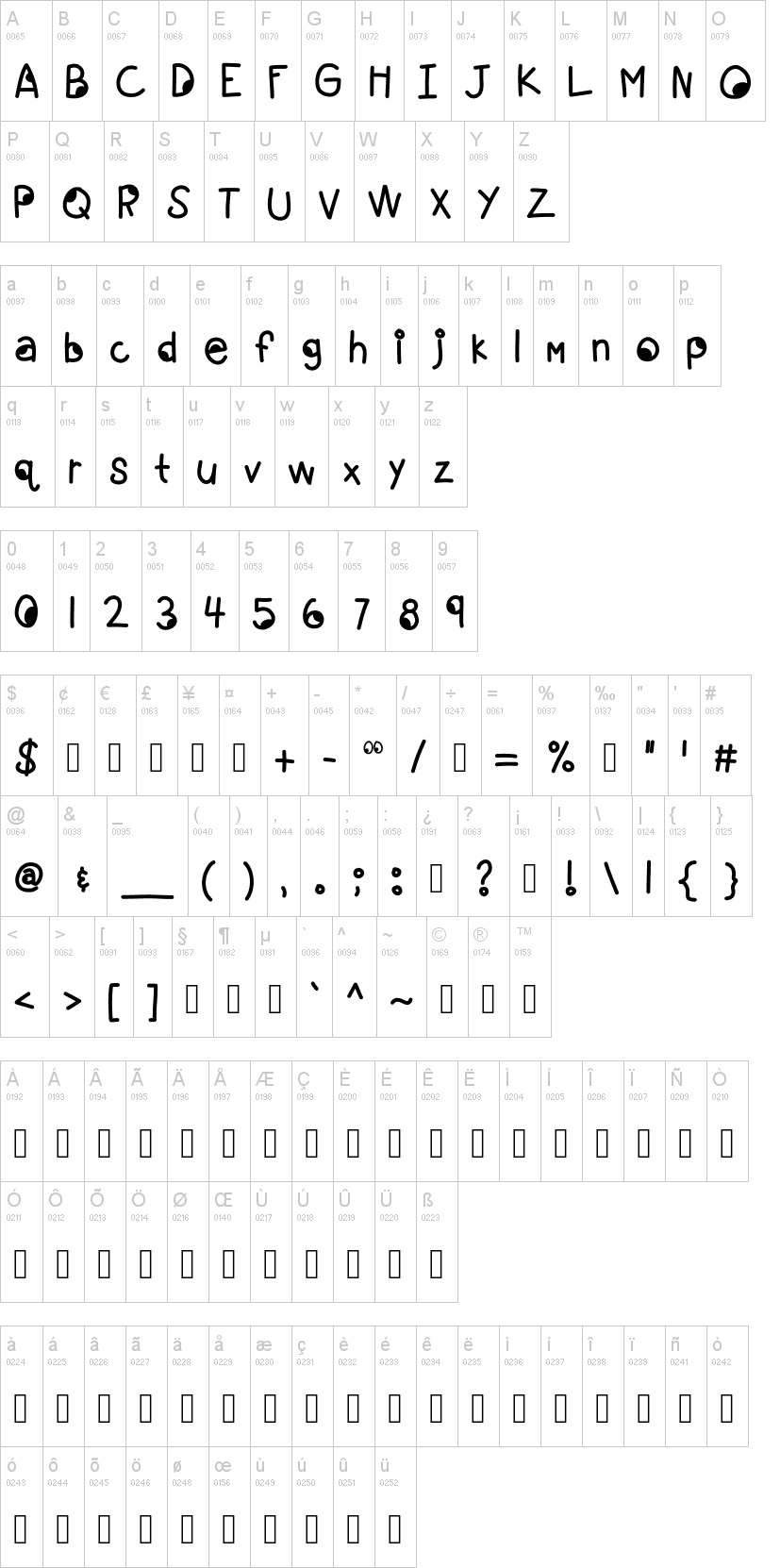
KB Googley Eyes
KB Googley Eyes 是一种手写风格的字体,其特点是所有字母都具有弯曲的形状,仿佛是一个孩子的手写字。该字体有着非常可爱、有趣的感觉,适合用于萌宠、儿童或其他需要强调可爱、天真无邪的场合。 该字体包括大写字母、小写字母、数字和一些常用标点符号,具有一定的可读性。它的线条流畅、轻盈,非常适合应用于卡通、游戏、广告等场合。该字体的设计者是K26 Fonts,它可以在许多免费字体库中免费下载和使用。
KB Googley Eyes是一款非常不错的手写艺术字体,具有很好的视觉感,适合于文化类的宣传设计、商业类品牌的广告和产品包装设计以及个性化文字排版等较多场景。
KB Googley Eyes字符映射图